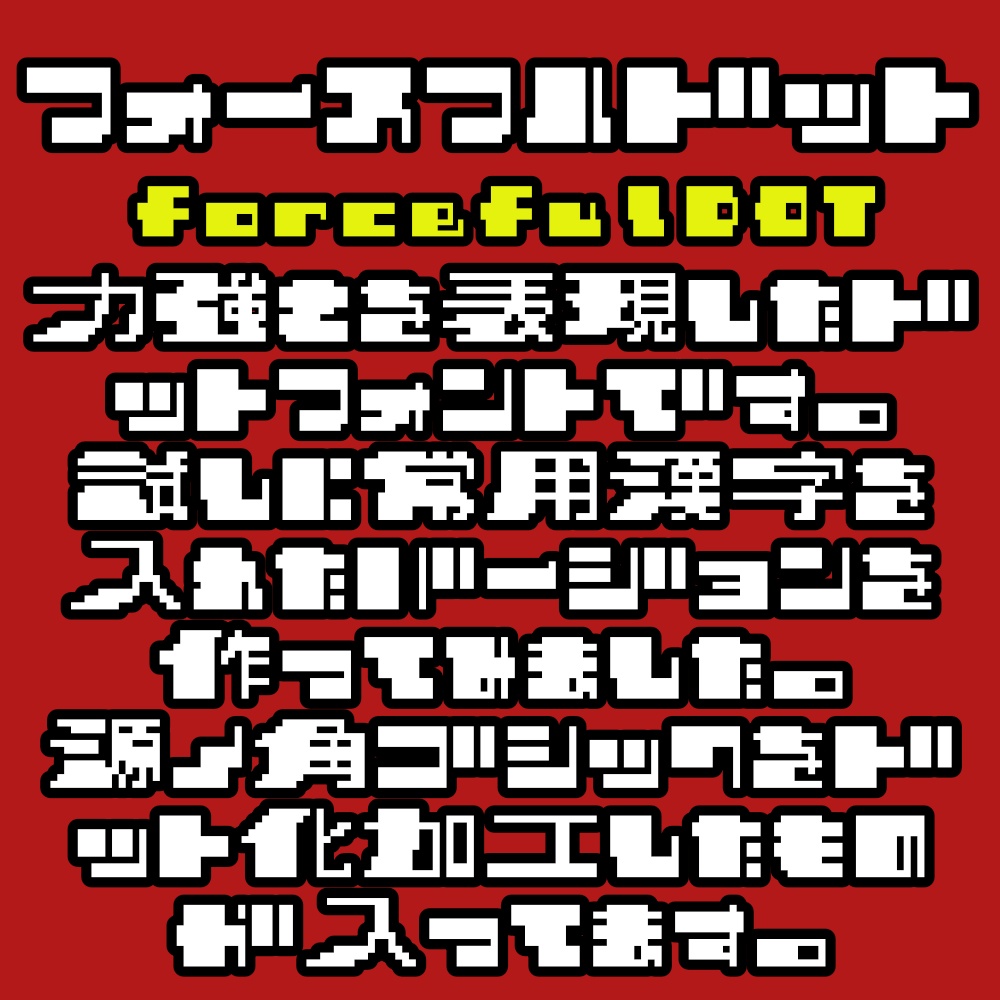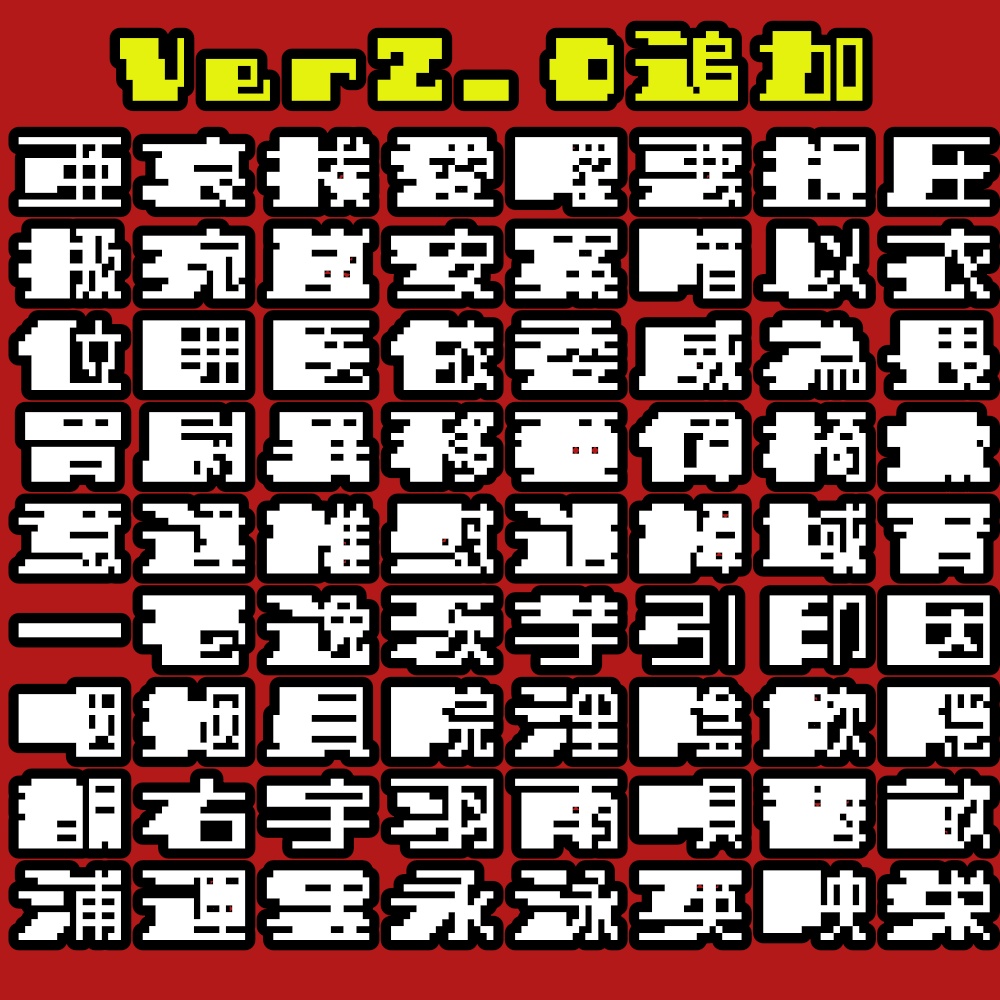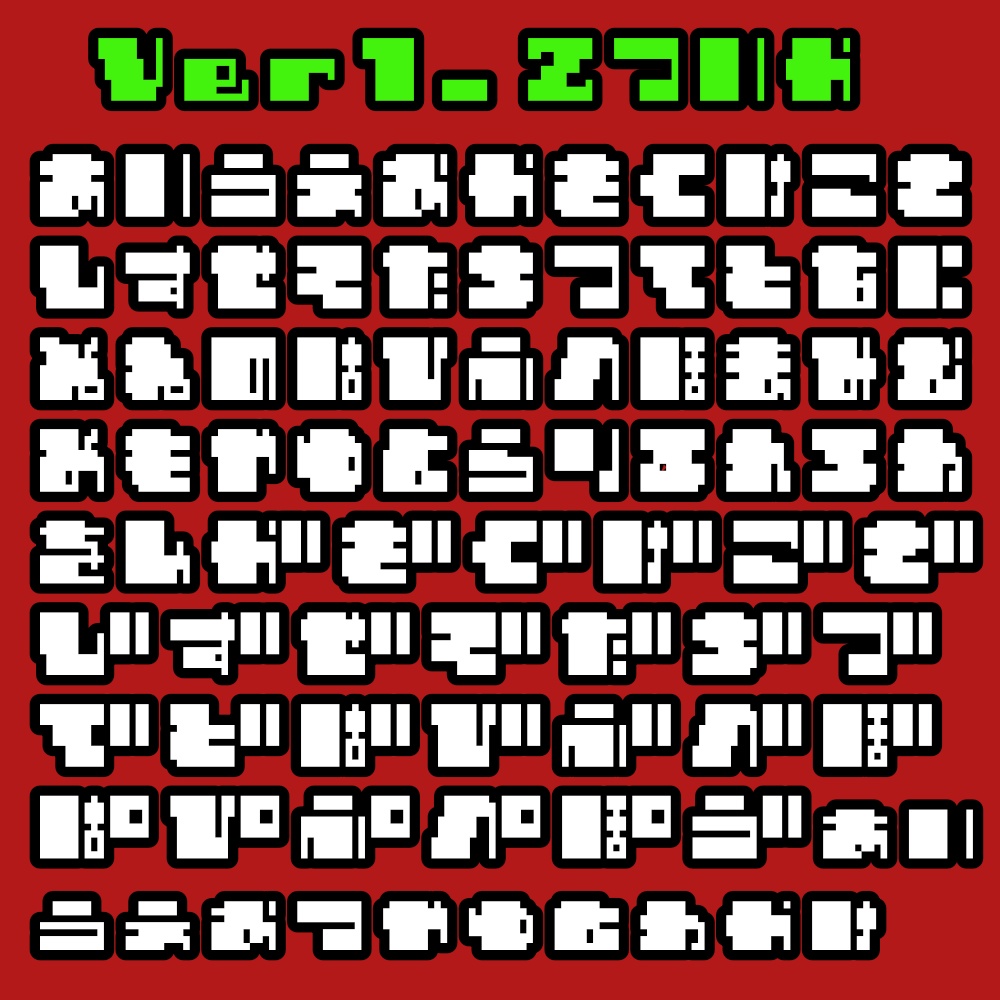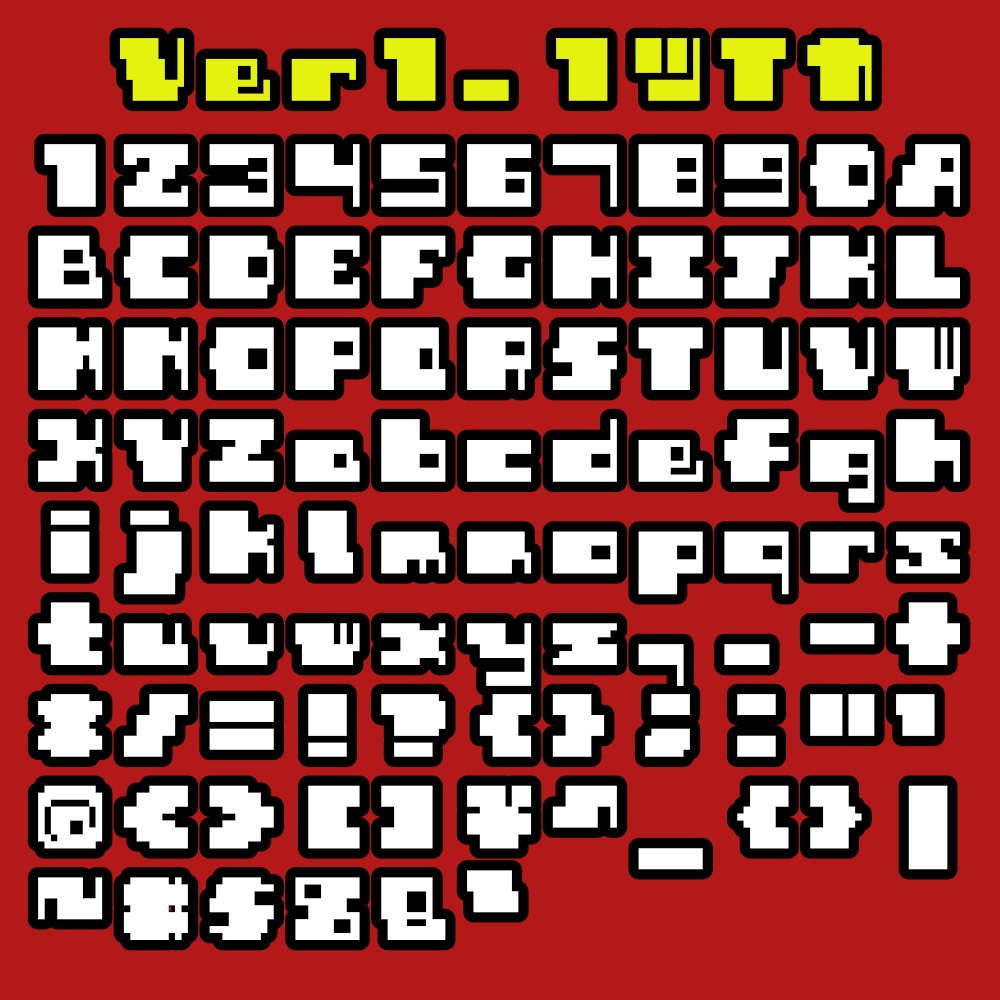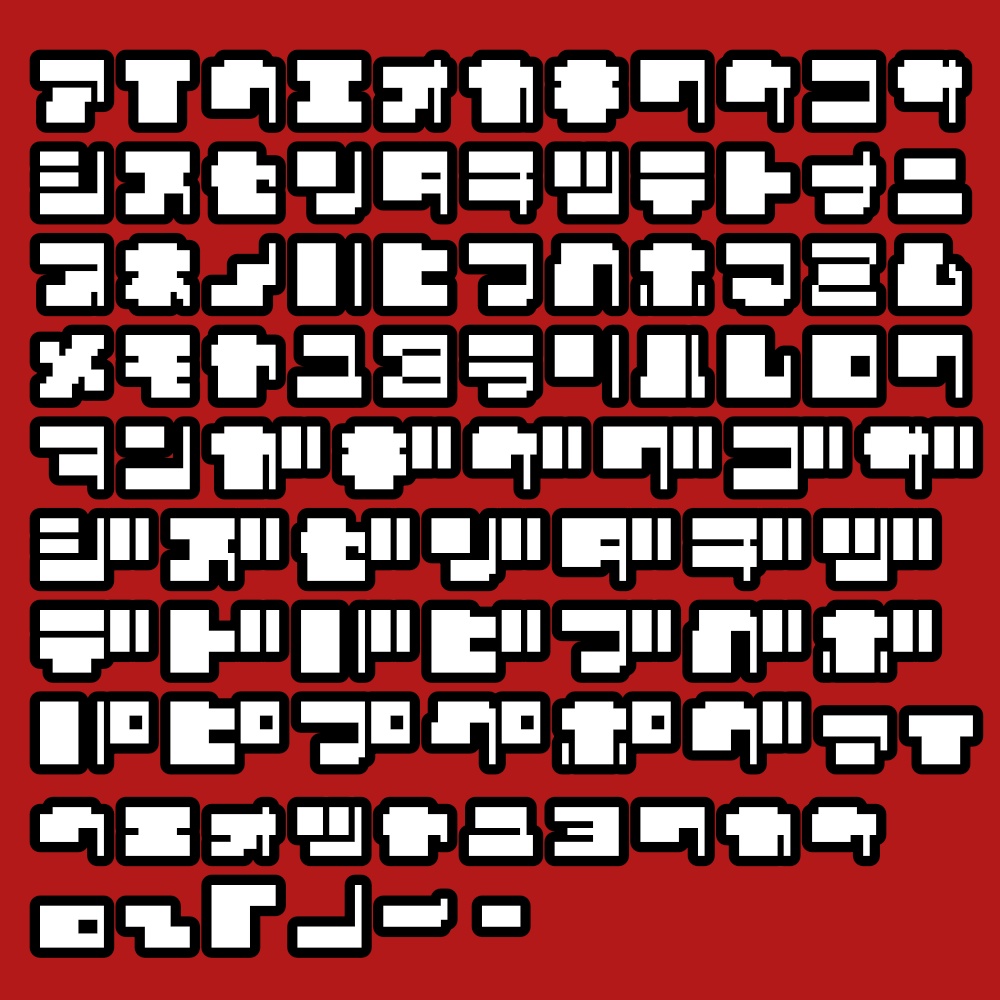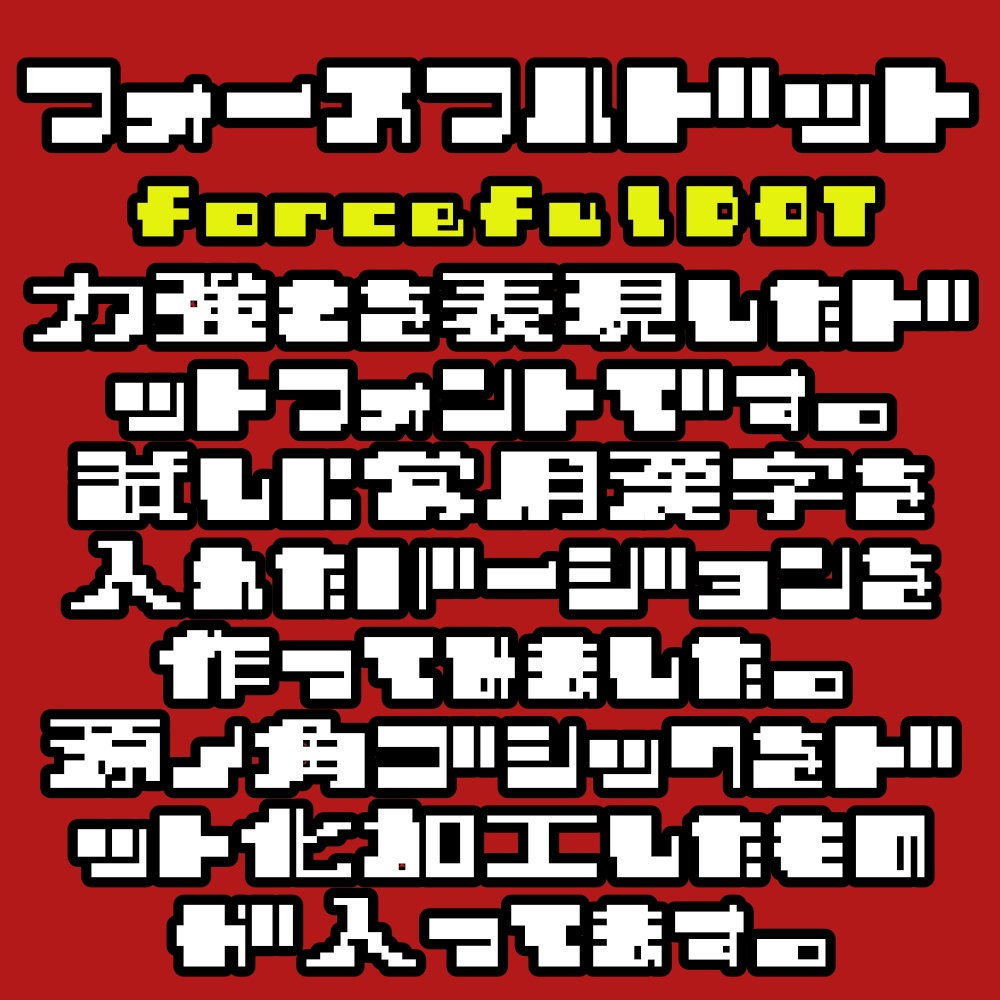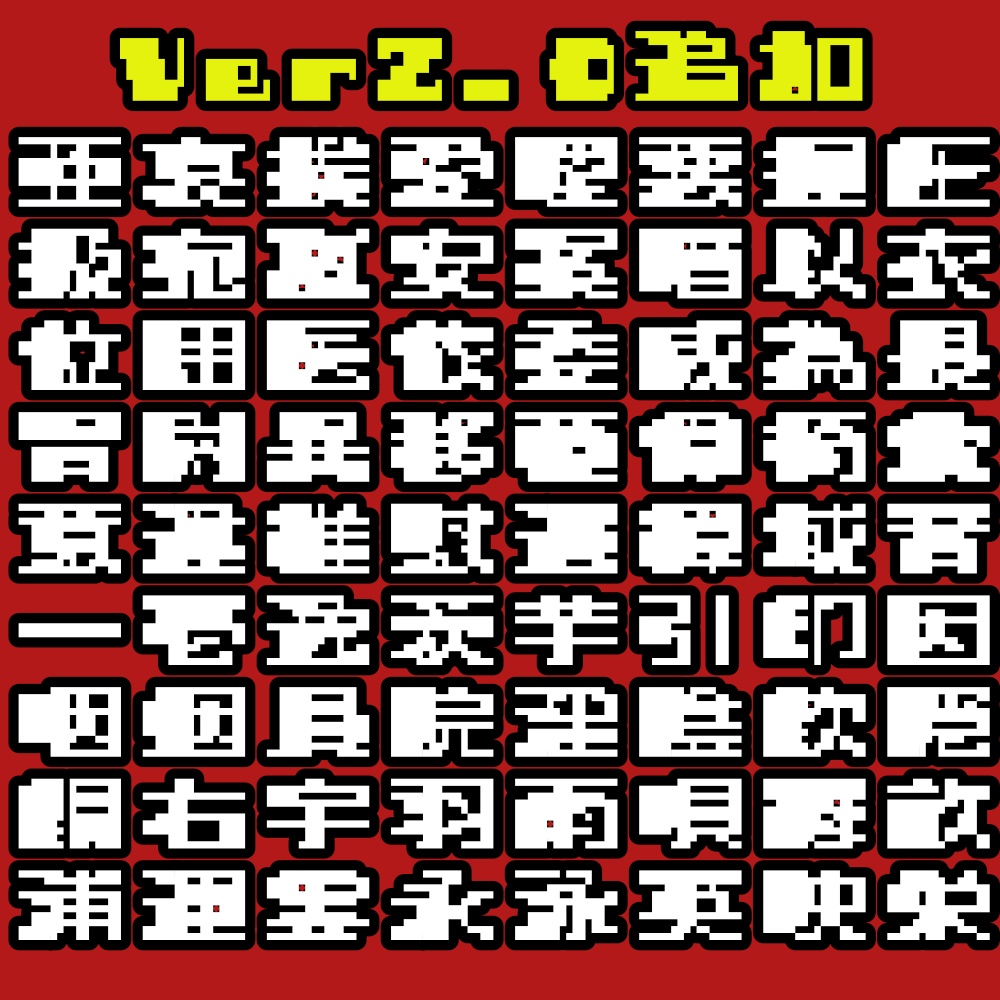
フォント フォースフルドット
ドットフォントを作ろうと考えました。 力強くするため、なるべく太字になるよう構成されています。 漢字部分においては源ノ角ゴシックをベースにドット化しています。 読めなくなっている漢字が多数存在します。これは一括処理をしているためであり、個別修正することはありません。 バージョンのbeta表記が外れる事はおそらく無いでしょう。